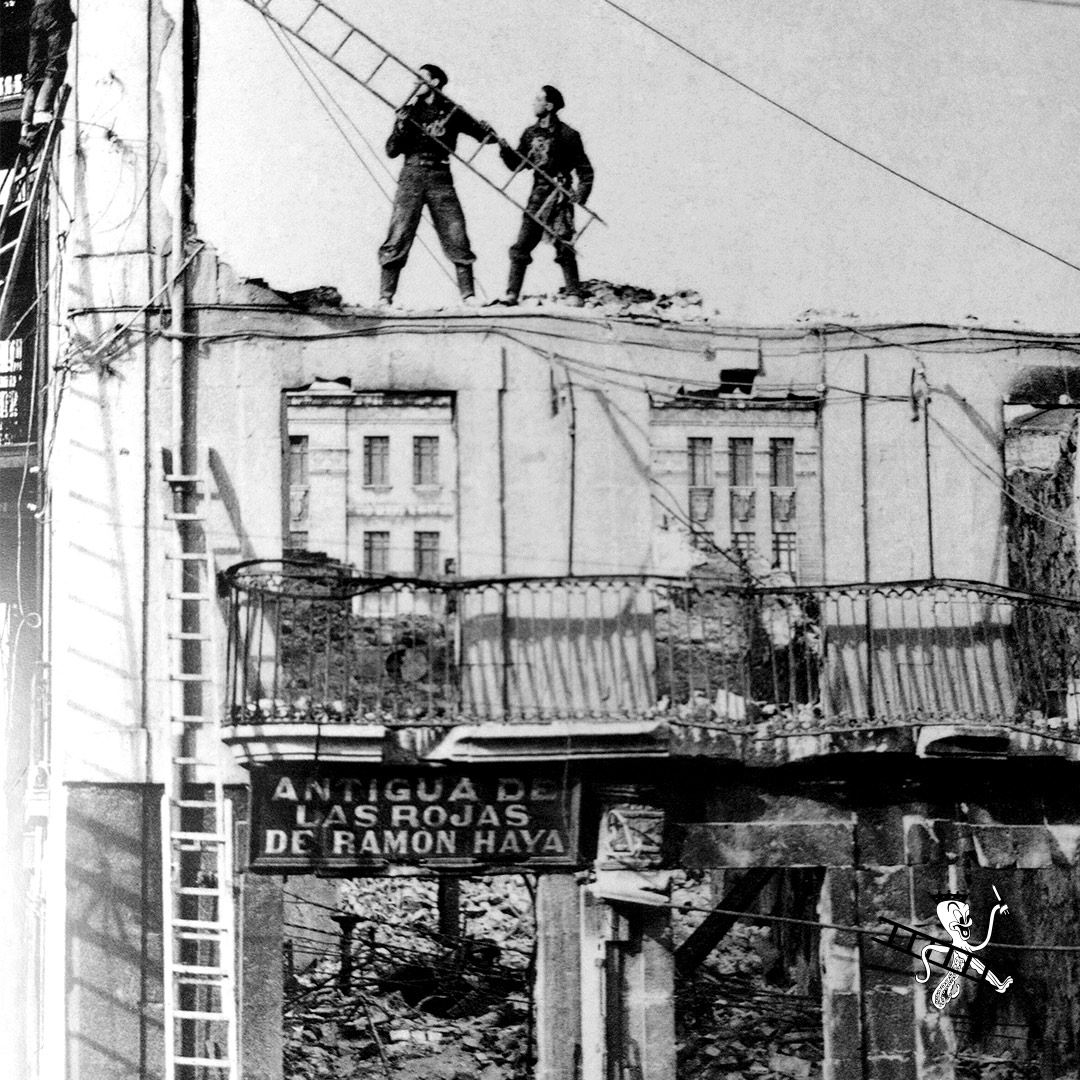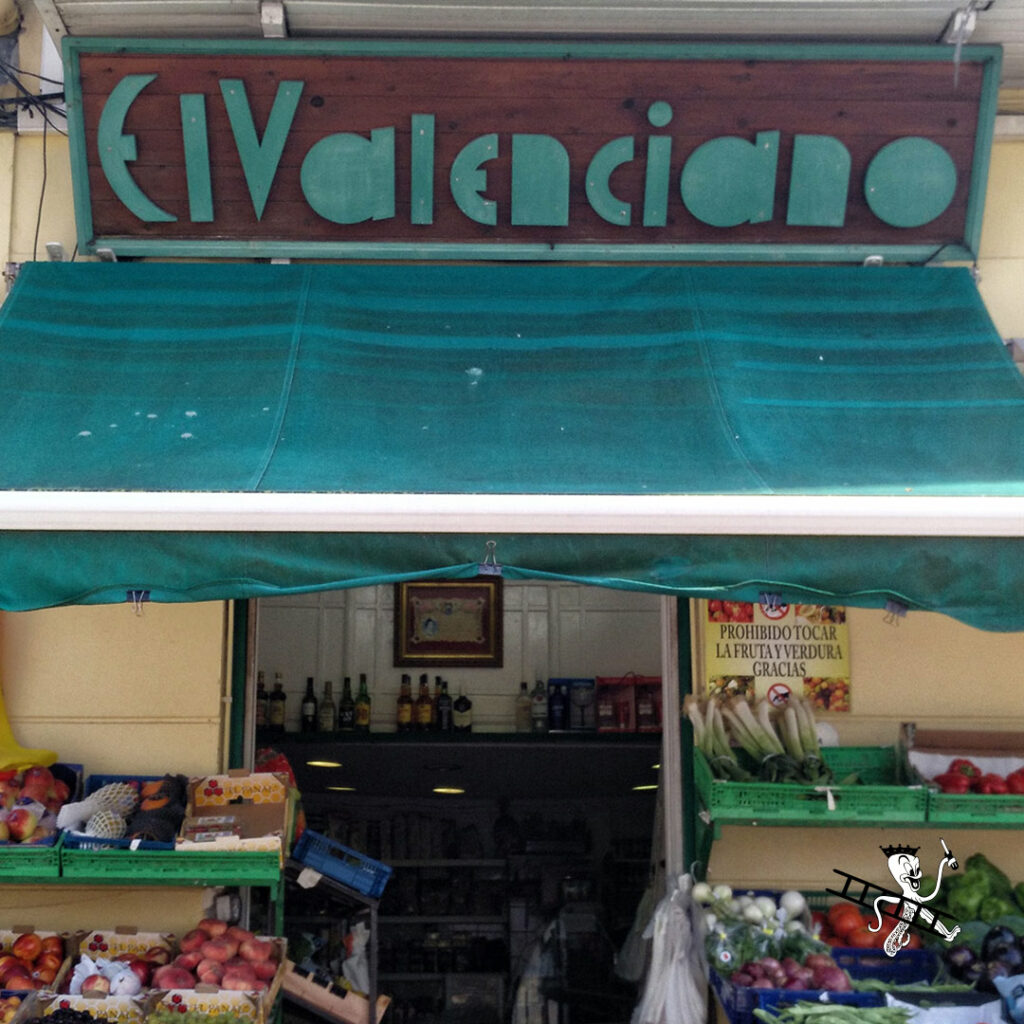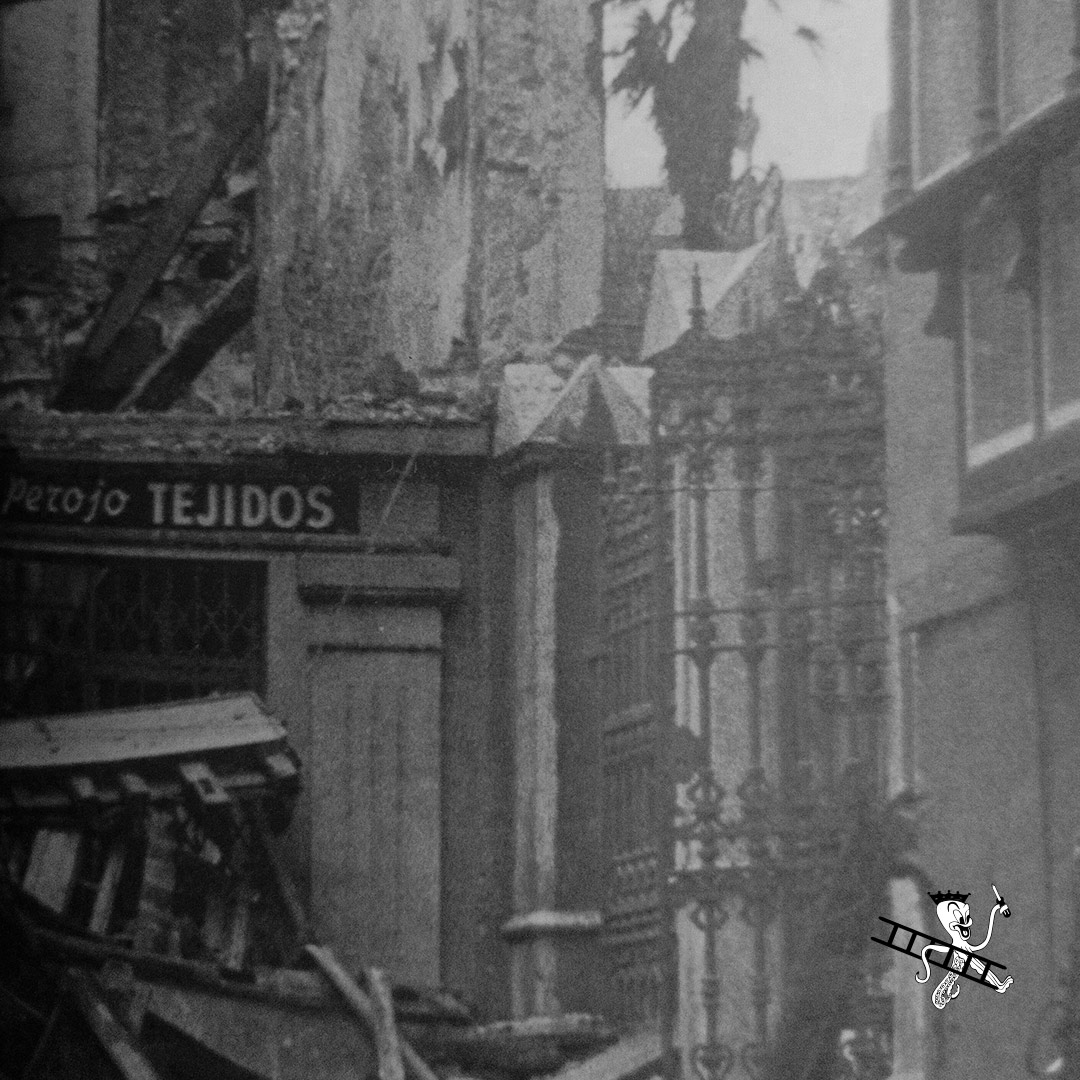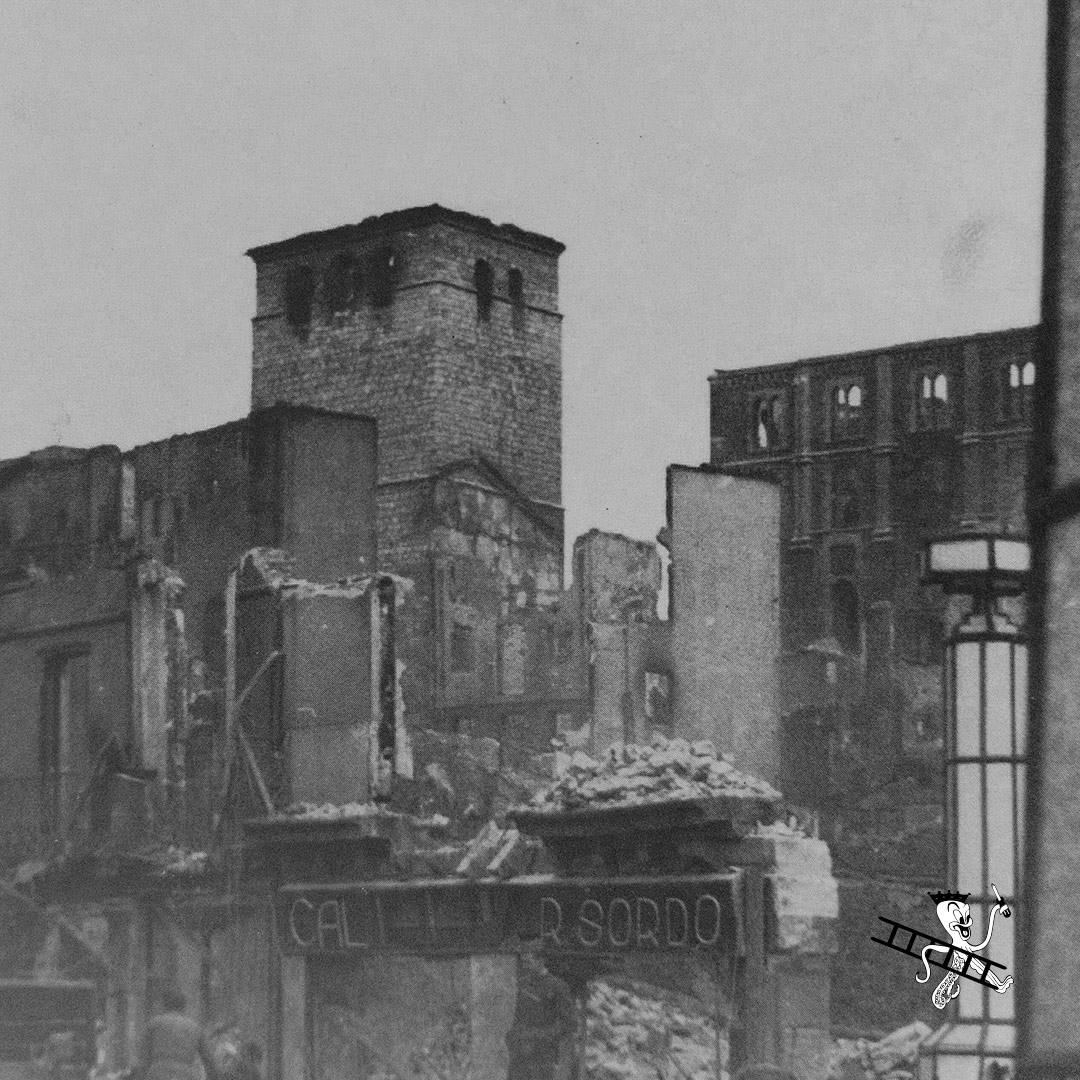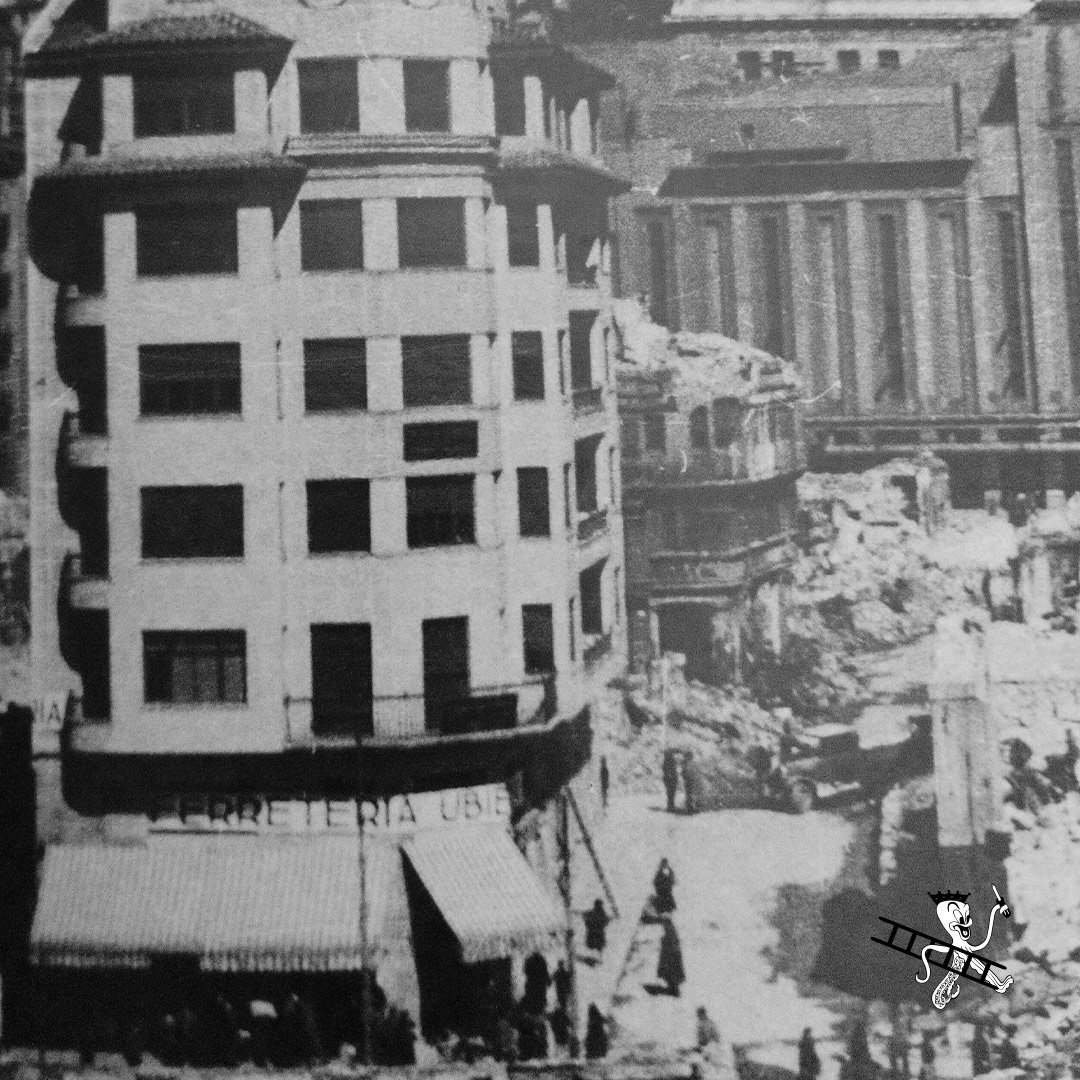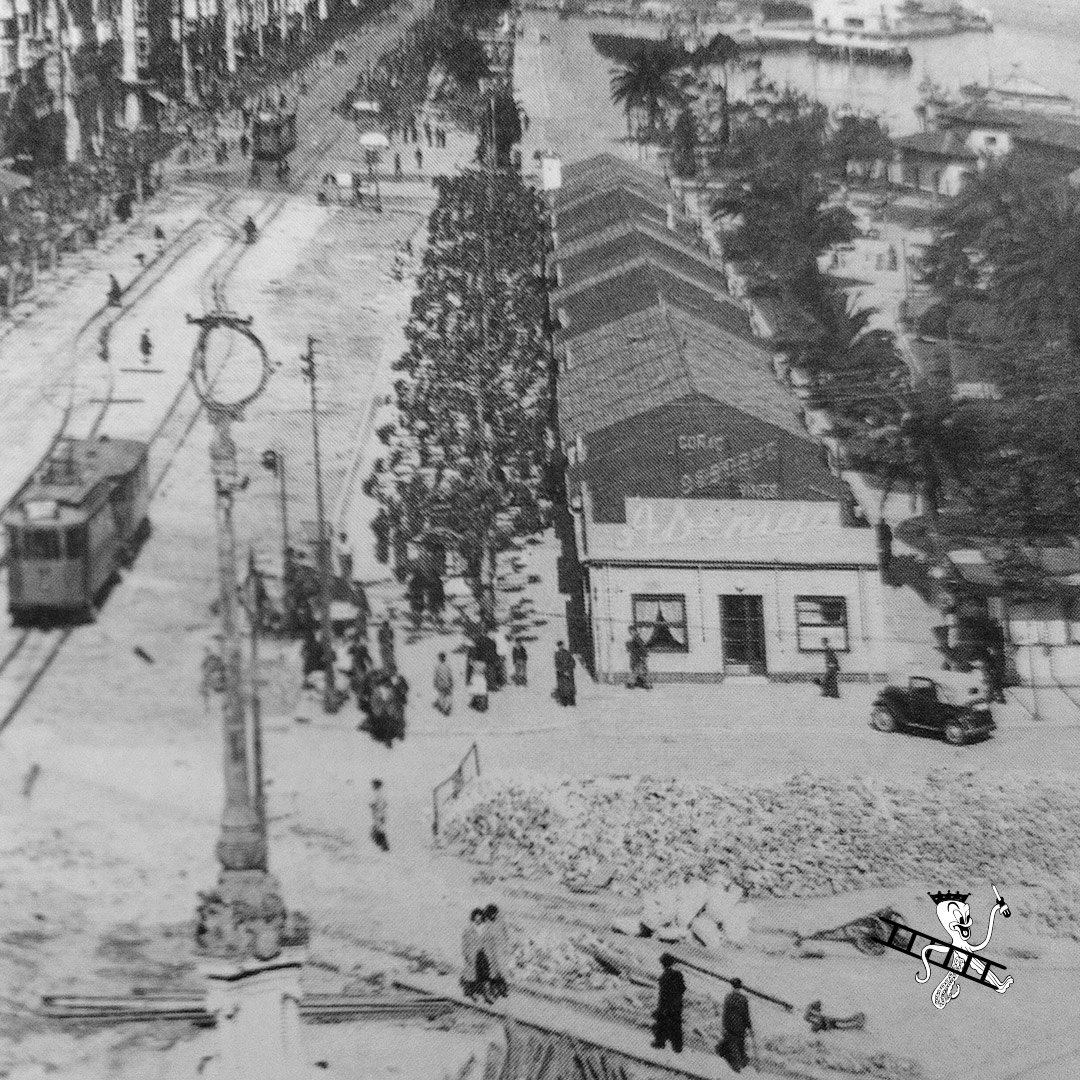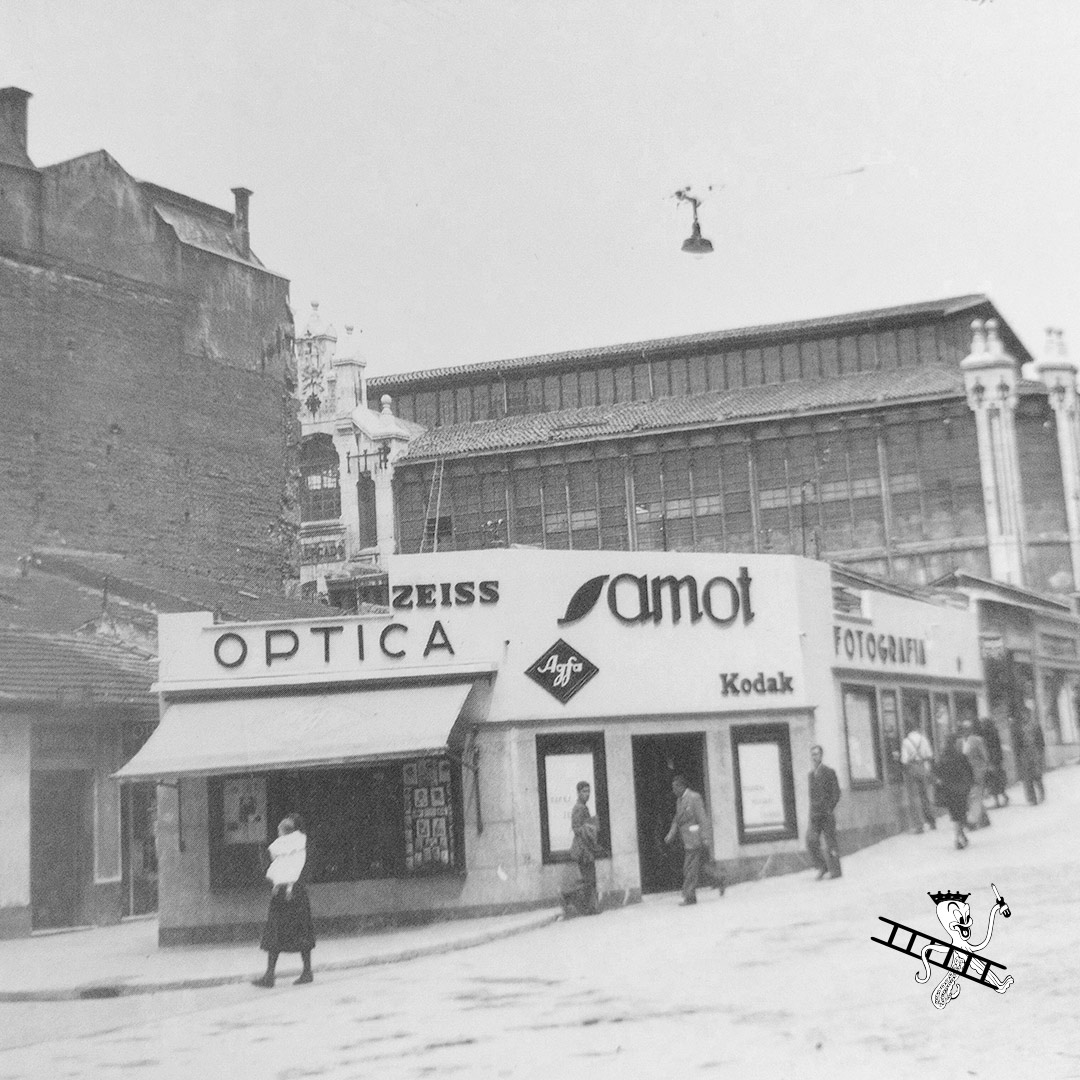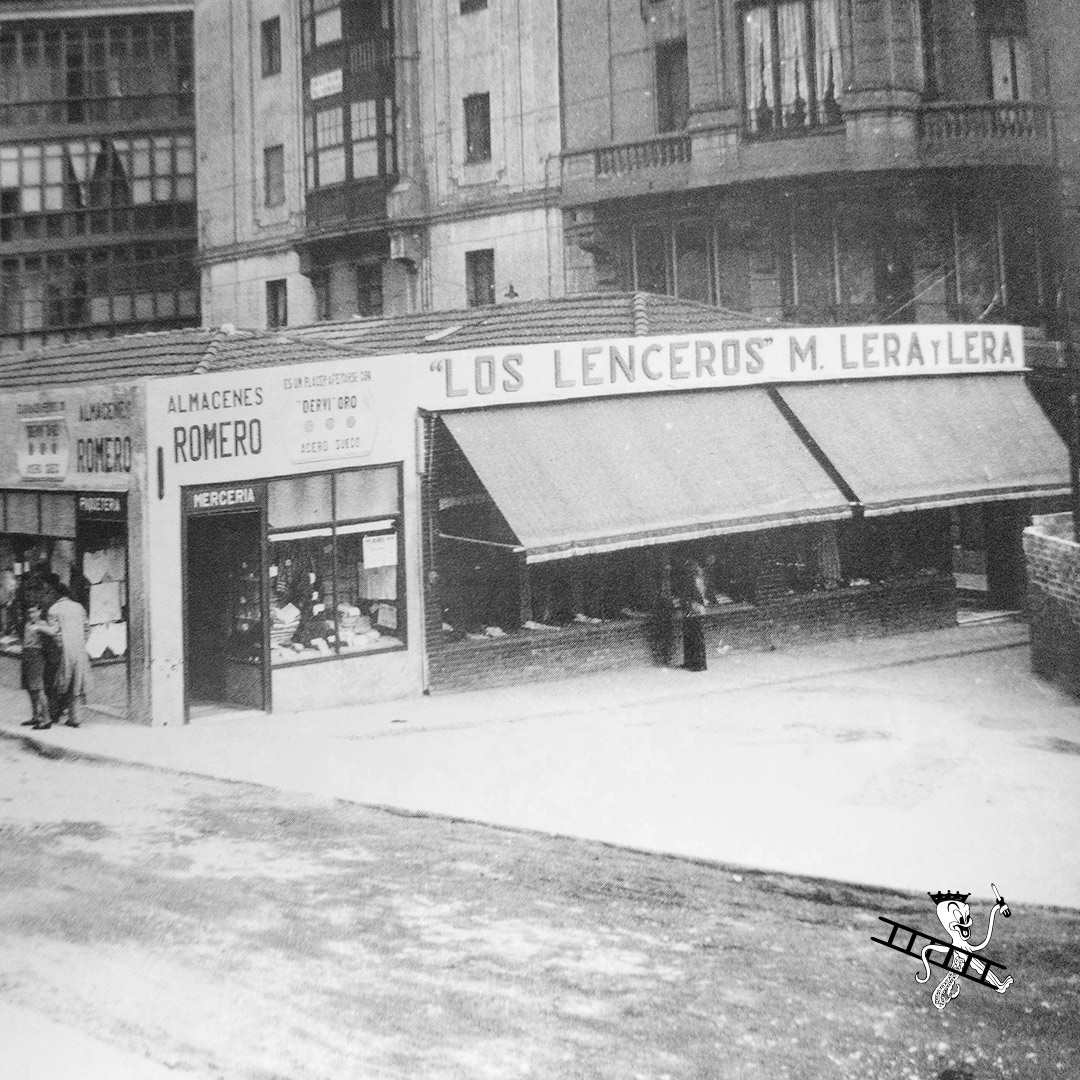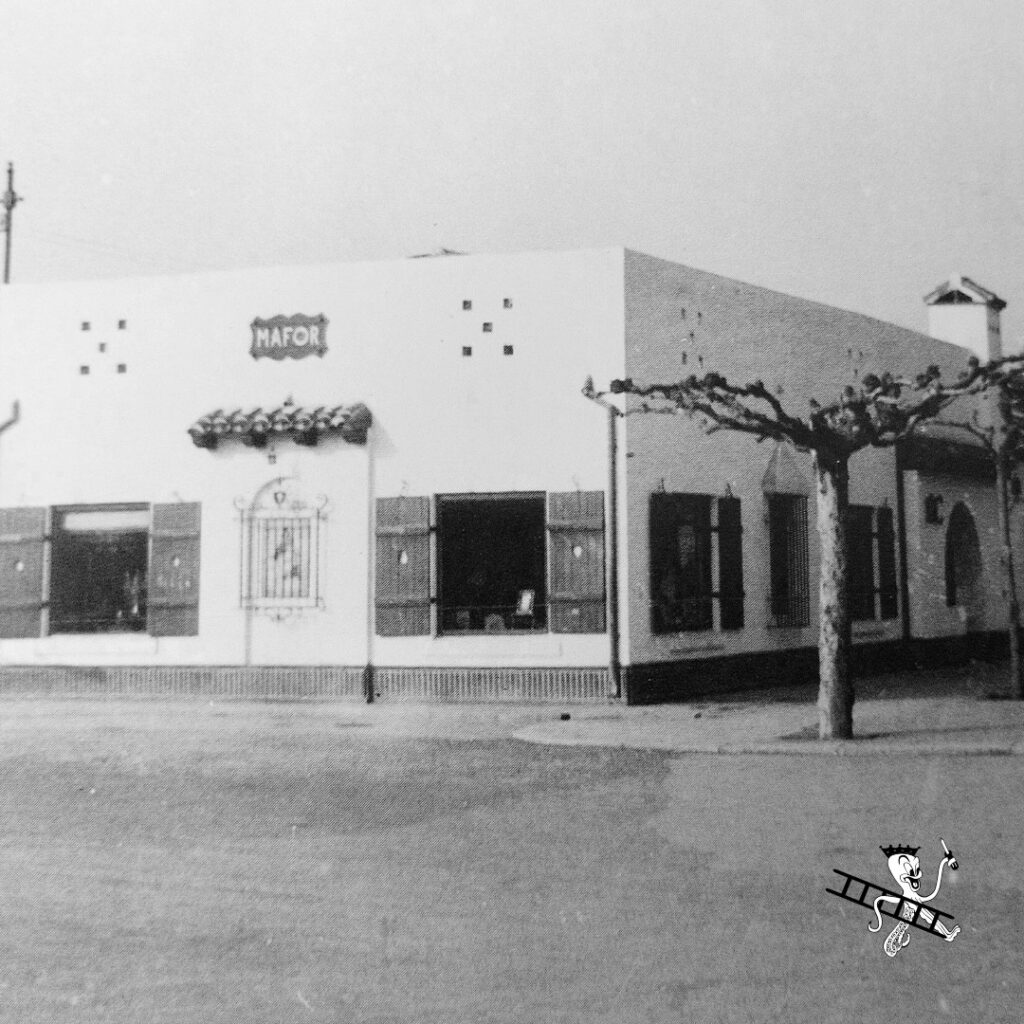
Patrimonio resiliente ante catástrofes y conflictos
Hoy 18 de abril se celebra el Día Internacional de los Monumentos y Sitios (DIMS), una iniciativa de ICOMOS que comenzó en 1982 con el objetivo de sensibilizar sobre la importancia del patrimonio cultural y la necesidad de protegerlo.
El tema de este año es «Patrimonio resiliente ante catástrofes y conflictos» y desde Santatipo no podíamos no acordarnos de nuestro Patrimonio Gráfico tras el Incendio del 15 de febrero de 1941 en Santander, que devastó el centro de la ciudad y más de 500 comercios locales fueron destrozados por el incendio.
El 17 de febrero en una reunión en el Ayuntamiento, el Alcalde Emilio Pino consciente del desastre que el incendió causó y las consecuencias que tendría, propuso la inmediata construcción de los barracones en todos los espacios libres de la ciudad para que comerciantes y artesanos pudieran instalarse e iniciar y dinamizar la actividad económica de la ciudad, por la importancia que esto tendría.
Así pues se comenzó la construcción de esos espacios, que tendrían todos los servicios básicos y elementos necesarios para los negocios y sobre todo, se comenzaban a instalar y pintar los rótulos identificativos para precisamente recordar la imagen previa al incendio. Alguno ha llegado a nuestros días, como el de “El Valenciano”, hecho en Madera y que se ve en la foto de archivo con un recuadro.
Muchos comercios se instalaron allí, hasta que tuvieron la oportunidad de irse a un local comercial propio de la zona reconstruida u otro espacio de la ciudad. Y otros, como hemos contado en alguna ocasión, se instalaron en los portales de los vecinos, como podemos ver hoy día con la Administración nº13.
Así pues, protejamos nuestro #PatrimonioGráfico porque es lo que nos hace ser comunidad y barrio, al formar parte de nuestras vidas, y a pesar de las catástrofes, como vemos es algo que surge rápidamente.